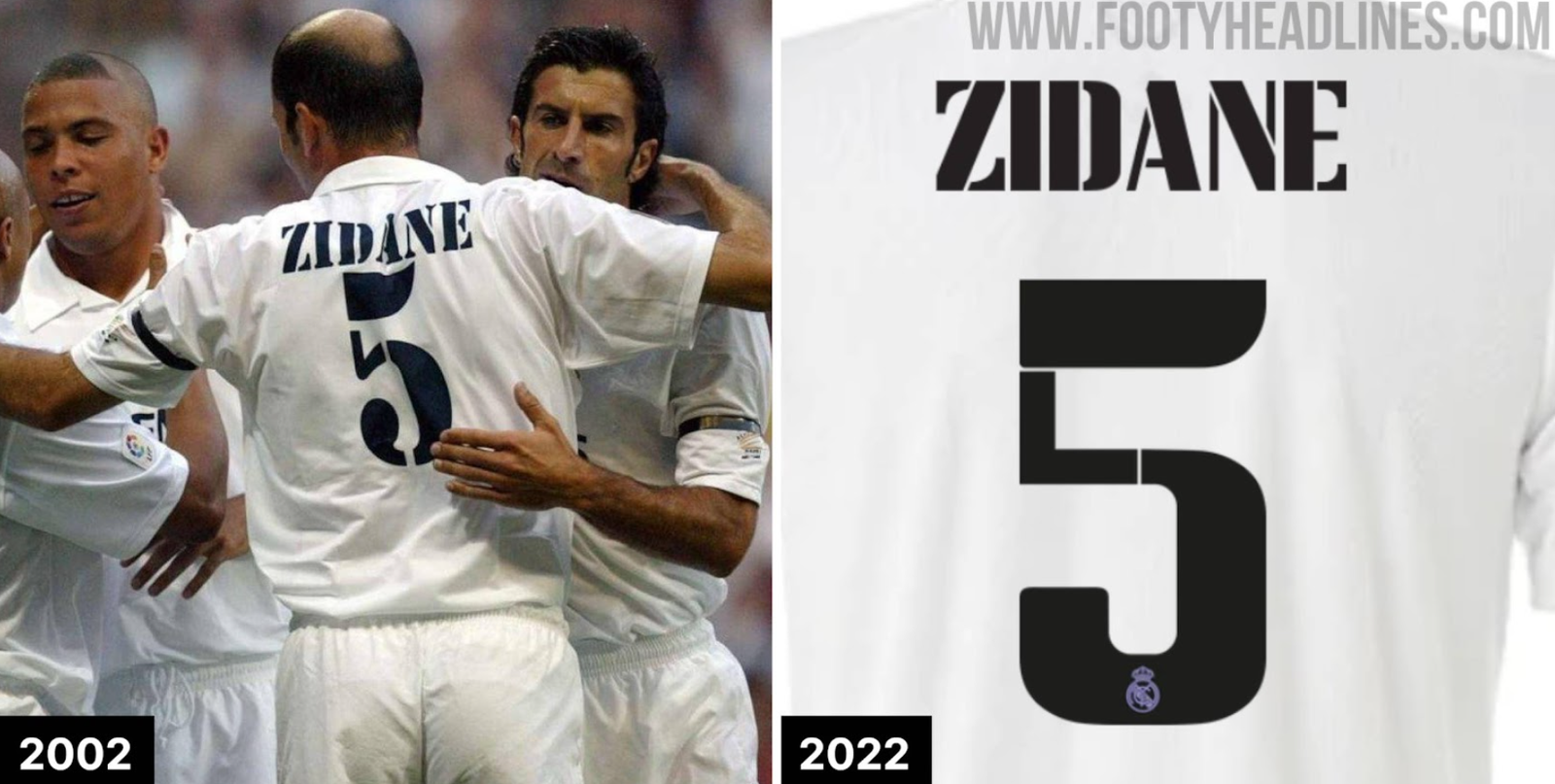
Vestir a camisa do Real Madrid é vestir a história do maior campeão da Europa. A temporada 2022-23 foi marcante não apenas pelo futebol de Vinicius Jr. e Benzema, mas também pela elegância do uniforme comemorativo de 120 anos do clube.
A Adidas trouxe para essa temporada uma tipografia exclusiva, utilizada nas noites mágicas de Champions League e na Copa do Rei. Agora, você pode aplicar esse mesmo visual lendário nas suas personalizações e designs esportivos.
Estilo Visual e Inspiração
A tipografia criada pela Adidas para o Real Madrid nesta temporada foge do padrão genérico de La Liga. Ela busca inspiração no estilo Art Déco e na arquitetura moderna do renovado estádio Santiago Bernabéu.
Com traços angulares e uma estética que remete ao clássico sem perder a modernidade, essa fonte se destaca pela sua presença imponente nas costas da camisa branca com detalhes em roxo. É a escolha perfeita para quem deseja fugir da fonte padronizada do campeonato espanhol e prefere a versão usada nas competições europeias.
Dica de Design: Esta fonte possui um visual “stencil” em alguns números. Ao vetorizar para corte, certifique-se de unir as pontes se desejar um visual sólido, ou mantenha o original para fidelidade total ao kit de jogo.